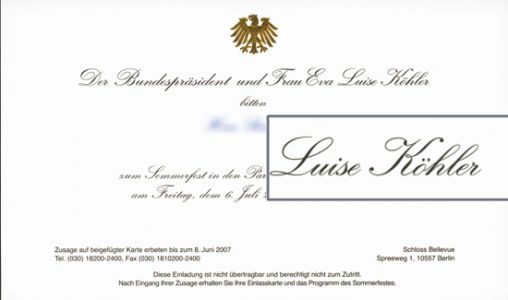
Horst Köhler liebt die Schreibschrift
ohne den Glücklichen nennen zu wollen, der hier eingeladen wurde, möchte ich doch einmal zeigen, wie Horst Köhler zu seinem Sommerfest einlädt. Er hat eine unverkennbare Neigung zu Schreibschriften, versucht das aber mit Arial (oder Helvetica?) zu vertuschen.
Der Adler ist vermutlich geprägt und mit Goldfolie gedruckt. Habs leider nur digital. Schönes Bonmot.
Ist Helvetica nicht sogar "Bundes-CI"?
Und für die Verwendung von englischer Schreibschrift gibt's wahrscheinlich ungeschriebene Protokollgesetze.
Kann man Drucksachen dieser Art überhaupt nach den geläufigen Kriterien beurteilen?
hat der Bund nicht die Demos und die Praxis im Einsatz? (Beides Schätzchen von meinem heimlichen Superstar Gerard Unger)
hehe, ich empfehle euch das sonderheft der ZEIT campus, dort ist
ein artikel über visitenkarten, unter anderem ist die karte
von angela merkel abgebildet, die sieht fast genauso aus, der adler ist
bloß nicht vergoldet.
in dem artikel erzählen zwei grafiker von jung von matt darüber was schriften
und papier so deuten, ich habe lange nicht so gelacht, so ein gelaber.